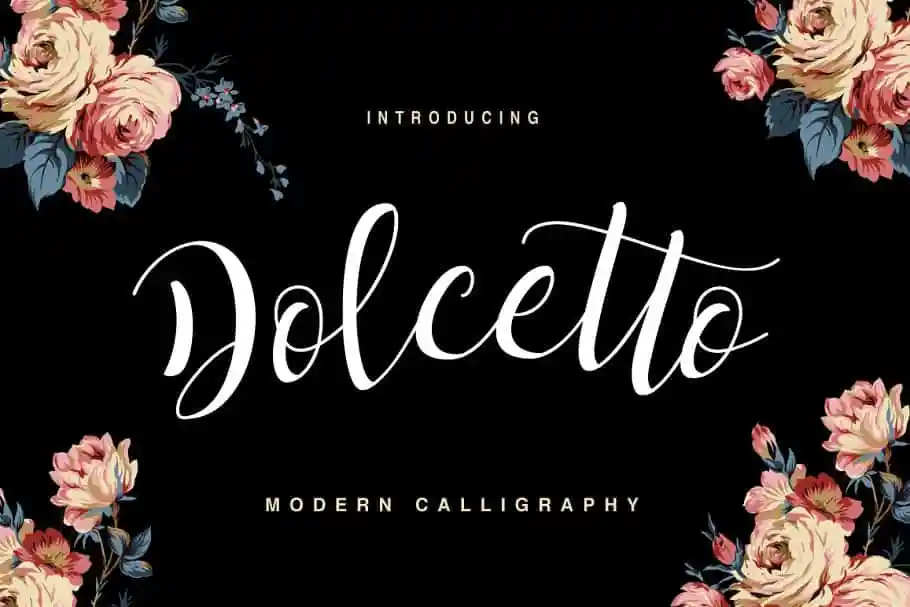
Dolcetto Script Font – Download Grátis
A Dolcetto Script é uma fonte tipográfica que oferece fluxos fluidos nos caracteres, perfeitas para criar mensagens atraentes, seja combinada com outros caracteres alternativos ou utilizadas de forma independente. Suas letras modernas e elegantes são como um registro precioso da arte do caligrafista, fornecendo uma variedade incrível de variações que ajudam a tornar seu projeto único e definitivamente personalizado. Desta forma, a Dolcetto Script pode ser usada em vários cenários gráficos. É perfeitamente adequada para logotipos, tags de nome com texto, citações escritas à mão, embalagens de produtos, materiais de mercadoria, mídias sociais e cartões de aniversário. A sua versatilidade e variedade permitirão que você crie designs únicos que se encaixam em qualquer projeto gráfico que precise de um toque de charme e estilo moderno.